俺のBakery&Cafe/俺の株式会社
「俺のBakery&Cafe」はクラフト墨が印象的な俺の株式会社が展開する俺の系パン屋。
俺のBakery&Cafe 新宿京王モール
岩手県のなかほら牧場のこだわりの牛乳と国産小麦・キタノカオリを使用した「俺の生食パン ~香~」や国産小麦・ユメチカラを使用した香り高い「俺の生食パン ~夢~」、白ワインの発酵種を使用して作られたトースト専用パン「山型の食パン」など「俺のBakery&Cafe」こだわりの食パンをはじめ、人気の各種サンドイッチが販売されている俺のBakery&Cafe 新宿京王モール。
俺のBakery&Cafe フルーツサンド
フルーツサンドはバニラビーンズのカスタードクリームに5種類の果物を贅沢に散りばめた、リッチな仕上がりのフルーツサンド。生食パン『香』の甘さともちもち感じゅわっと広がる果物の甘酸っぱさで1度食べればきっと虜になるサンドイッチ。
俺のBakery&Cafe 小倉と有塩バターのサンドイッチ
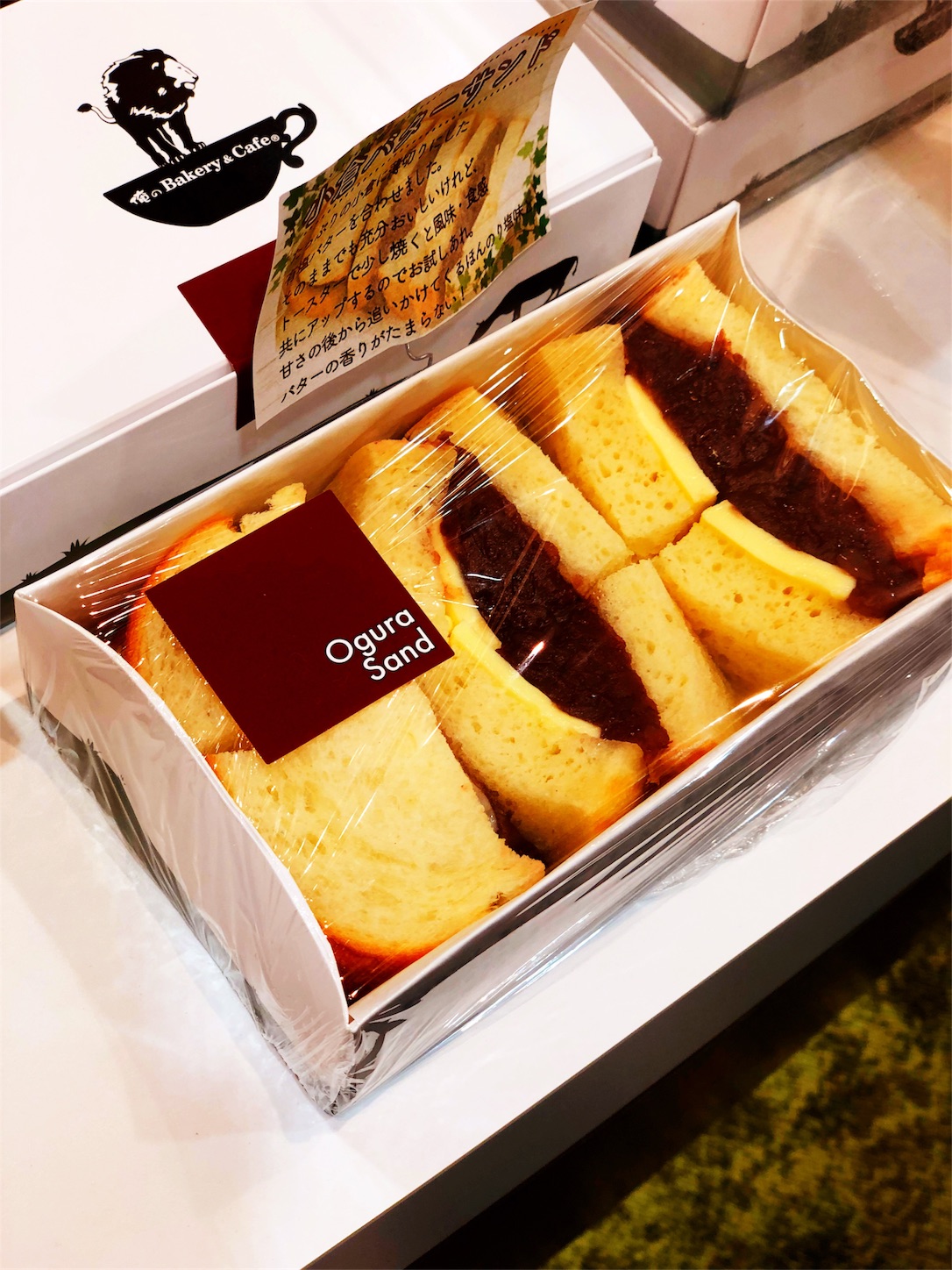
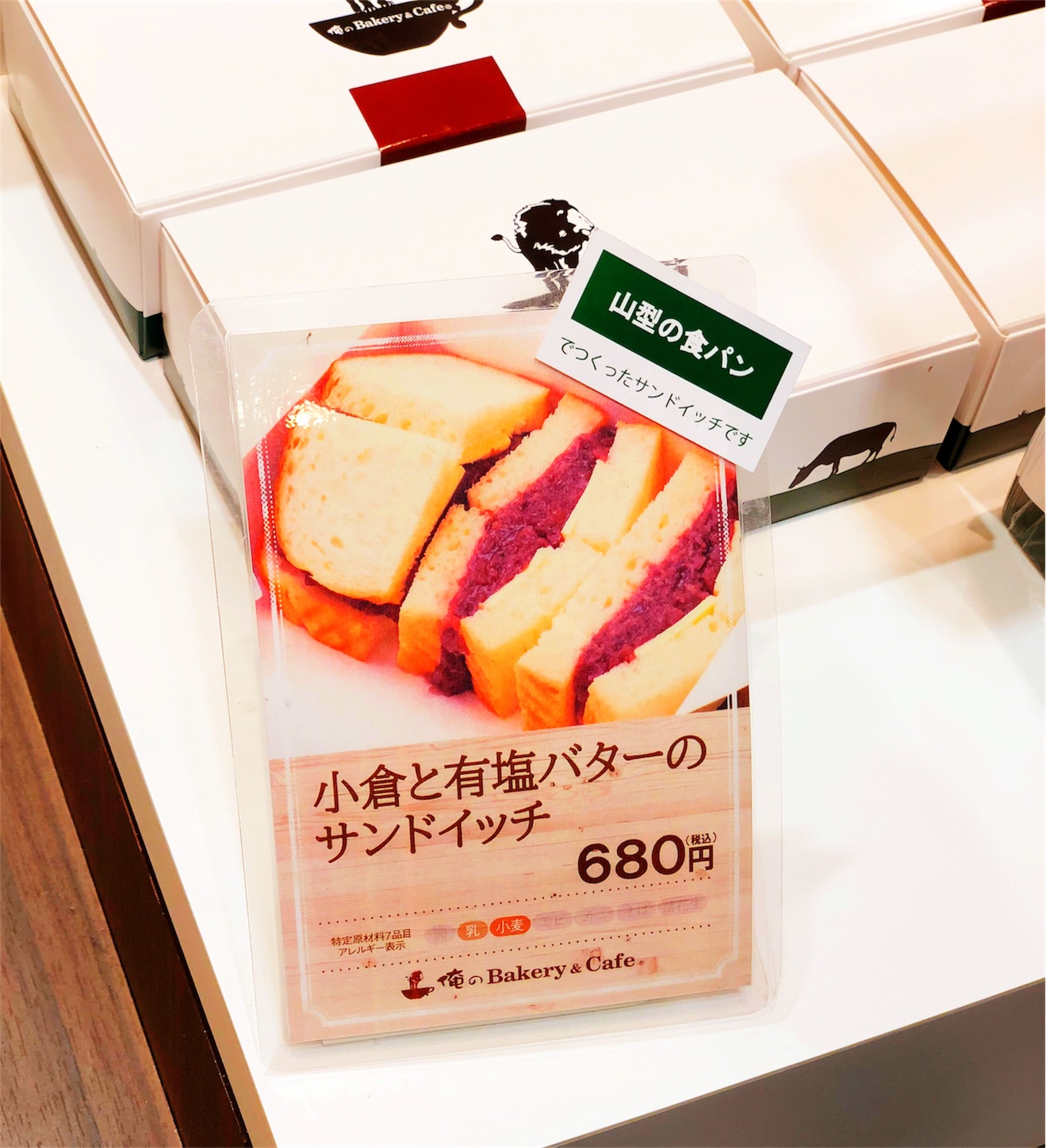
小倉と有塩バターのサンドイッチは、たっぷりの小倉に薄切りした有塩バターを合わせた、甘さの後から追いかけてくるほんのり塩味バターの香りがたまらないサンドイッチ。そのままでも充分美味しいが、トースターで少し焼くと風味・食感共にアップするのでオススメ。
俺のBakery&Cafe 新宿京王モールでサンドイッチを購入
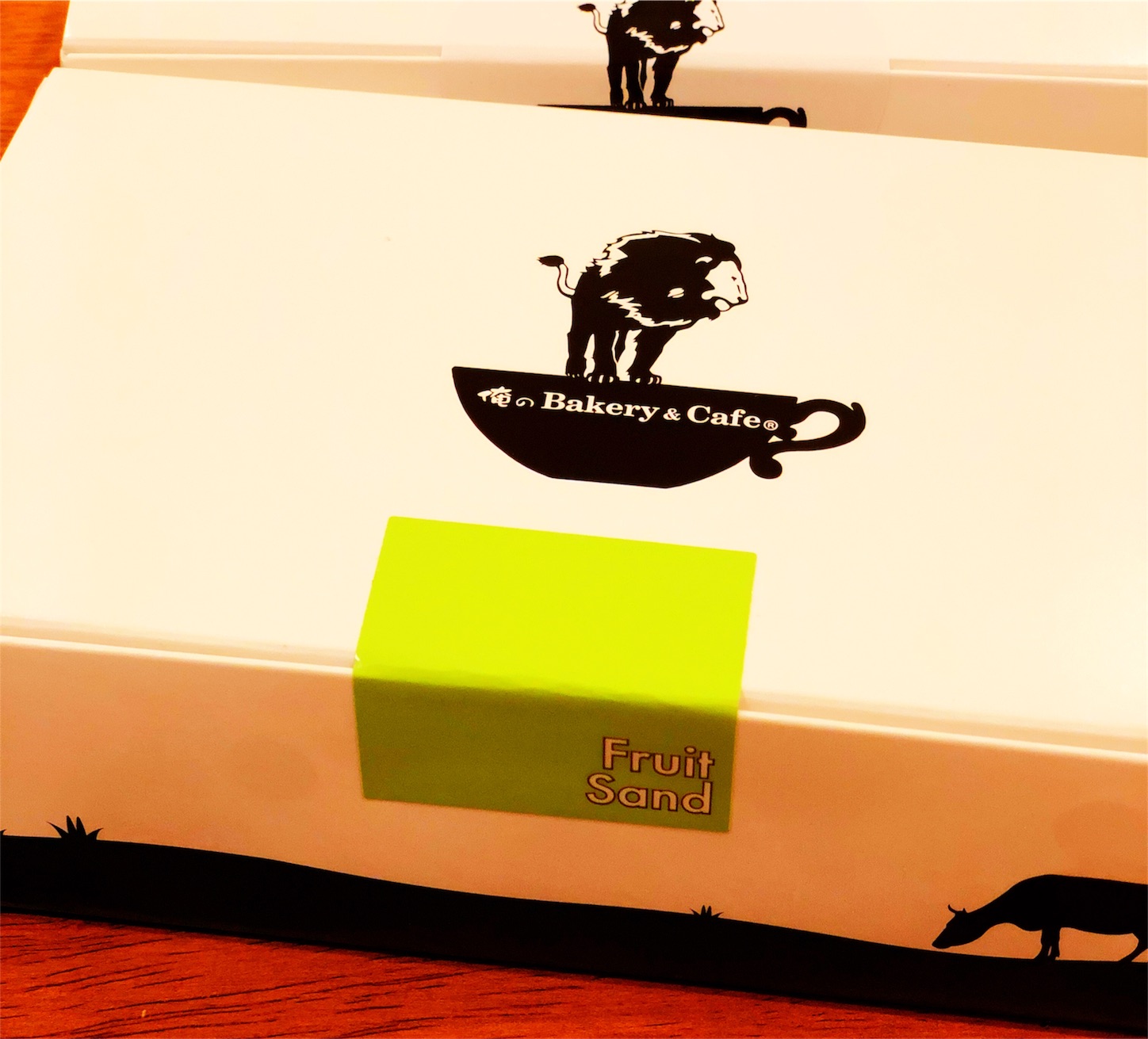
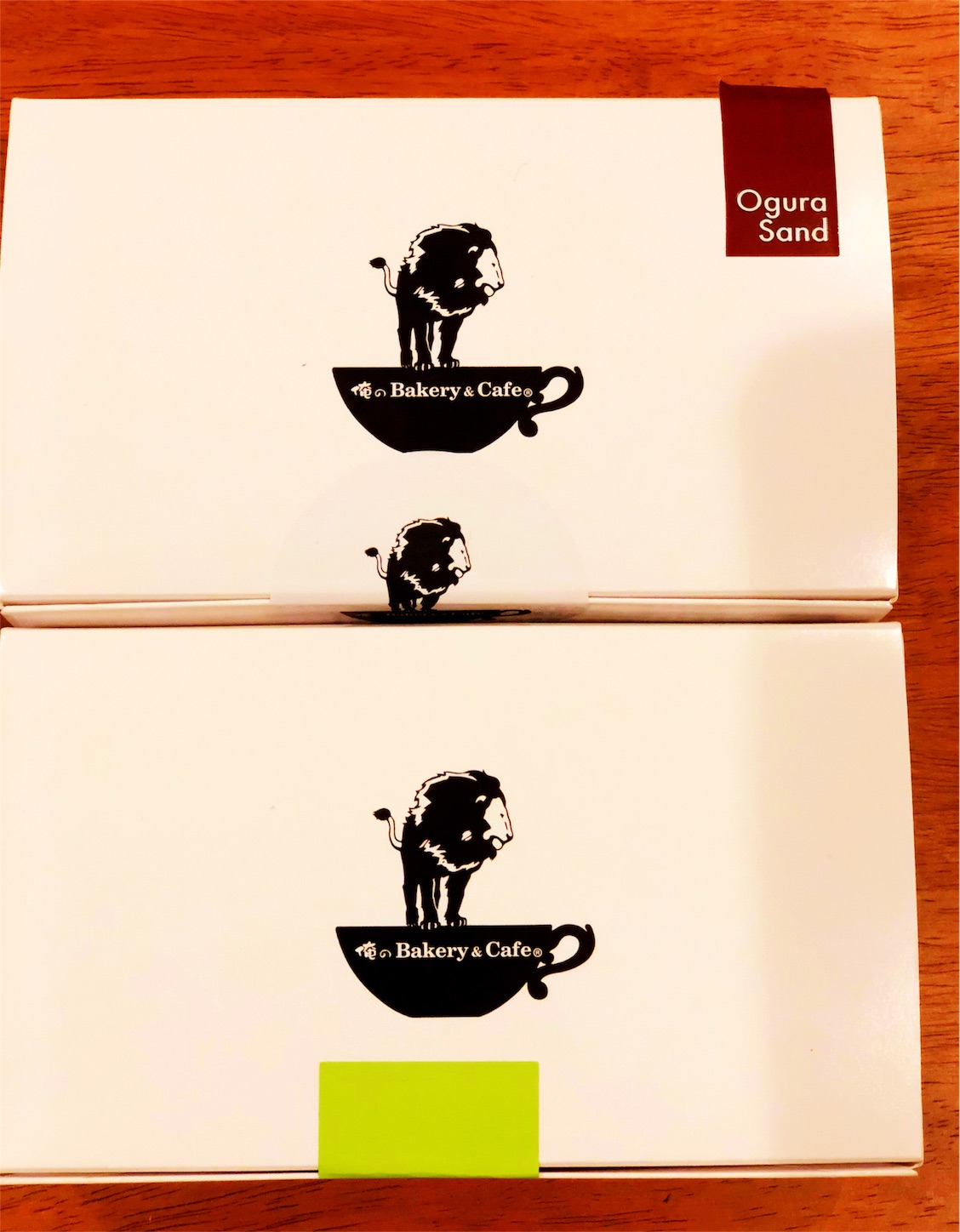
購入した箱にはOgura SandとFruit Sandと書いてあるが、実は…。
▼1つは確かにFruit Sandを購入していた。
▼もう1つは実は3種類の味が楽しめる欲張りサンドイッチだった。
小倉と有塩バターのサンドイッチ、ポテトサラダのサンドイッチ、厚焼き玉子のサンドイッチの3種類が入ったサンドイッチ。
▼実食!
▼領収書にもクラフト墨がしっかり印字されている。
俺のBakery&Cafe恵比寿店
恵比寿ガーデンプレイスにある「俺のBakery&Cafe」に行った。いつも行列が出来ていたのをしり目に散歩していたので恵比寿ガーデンシネマで「僕と世界の方程式」を観賞したついでにこれ幸いと訪問してみた。
俺の生食パン
俺の生食パンは、国産小麦やなかほら牧場の脱脂乳といったこだわり抜いた素材を使用したきめ細やかでしっとりとしていると同時にふんわりした弾力も兼ね備えた極上の食パン。焼かずにそのまま食べるのがおすすめ。 テイクアウトも可能だが、大人気のため、いつも行列が出来ている。
グラスフェッドバターコーヒー
グラスフェッドバターコーヒーを注文した。グラスフェッドとは家畜の飼育方法のひとつで、牧草だけで家畜を育てることをグラスフィーディングという。バターコーヒーダイエットとして毎朝、朝食の代わりにグラスフェッドバターを入れた コーヒーを飲むことが俄かに流行している。
イベリコ豚カツサンドイッチ
トーストも、こんがり焼けてました!
厚焼きたまごのサンドイッチ
まさに厚焼きという表現がぴったりの卵焼きに辛しマヨがよく合っていた。俺の生食パンはまさにふわふわで絶品。
俺のジャイアニズ
「俺の」系列というと立ち食いのイメージがあるが、俺のBakery&Cafeは普通に椅子があり座れる。テラス席もあるので春からはテラスで食べる食パンも乙な感じだ。
メニューから悩んだ末、俺の生食パン、山型の食パン、マスカルポーネとはちみつの食パンを食べ比べできる「こだわり食パンの食べ比べ」を選択するも…、売り切れ。
売り切れの無念さを抱えたままガッツリ系の「イベリコ豚カツサンドイッチ」「厚焼きたまごのサンドイッチ」を食す。
特に「厚焼きたまごのサンドイッチ」とグラスフェッドバターコーヒーによくあった。
来訪時には
俺の生食パンに限らず、
山型の食パンだって、
マスカルポーネとはちみつの食パンに至っても、
俺のパンは俺のパン
お前のパンも俺のパン
とジャイアニズムを発揮して
朝早めに並んでしっかり食パンを頬張りたい。
俺の株式会社公式アプリ【俺のアプリ】も登場
俺の株式会社公式アプリ【俺のアプリ】でも「クラフト墨」が採用されている。
「俺の株式会社」にクラフト墨が採用
俺のBakery&Cafeを含む「俺の株式会社」ではダイナフォントのクラフト墨が採用されている。
クラフト墨
書道本来の構成や書き方に変化を加え、文字の面白さや破調を表現した書体。線の長さや「へん」「つくり」などの部首に字形を崩す程の変化を加えている。また空間の取り方も独特で丸く豊かな運びにより、かわいらしくリラックスした雰囲気が引き出され、墨字の躍動感も表現されている。